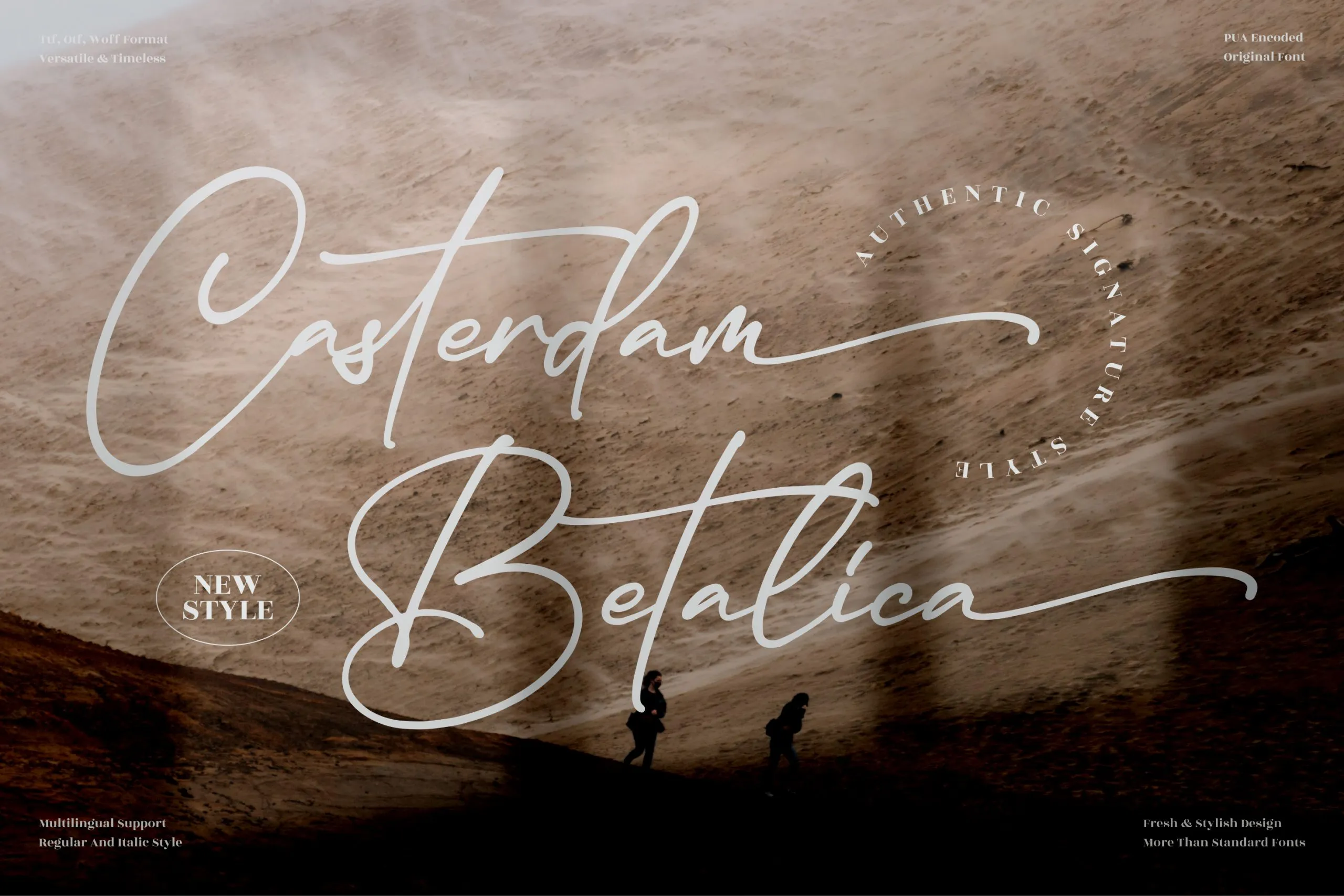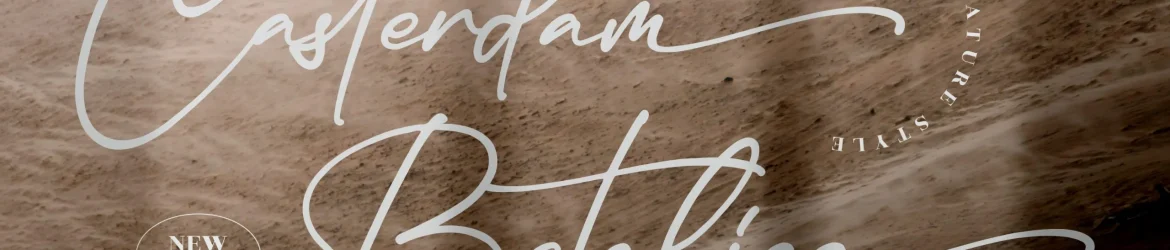
A Casterdam Baletica Font é uma elegante linha de fontes que foi especialmente projetada para adicionar um toque de sofisticação a qualquer projeto. Esta fonte escrita à mão é perfeita tanto para criações artísticas como para uso diário, oferecendo você e seus clientes uma maneira única e elegante de se expressar. Seja em sua marca pessoal ou no design do seu produto, essa fonte trará um toque premium aos seus projetos. Eles são ideais para aplicação em logotipos, embalagens de produtos, camisetas, adesivos, materiais promocionais e qualquer outro projeto que seja capaz de se beneficiar da sua personalidade única e sofisticada. Além disso, a perspectype trouxe uma fonte de escrita à mão para aqueles que desejam um toque delicado ou elegante em suas produções gráficas. Esta Casterdam Baletica Font é uma escolha perfeita para designers amantes do handmade.